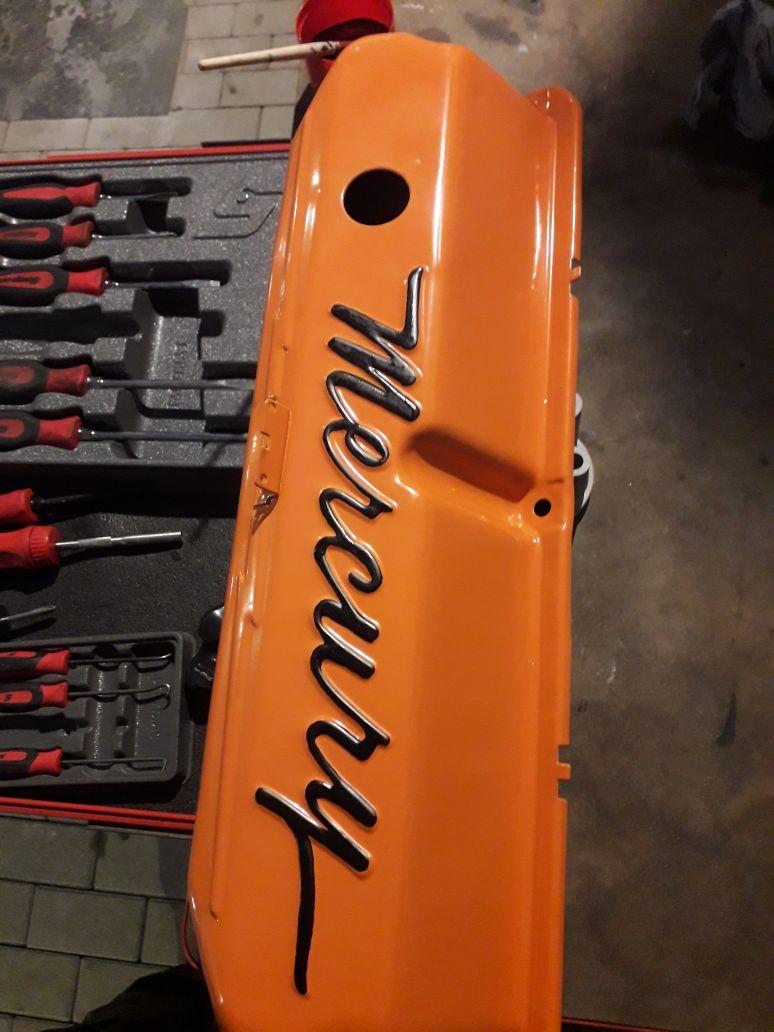
Suche Schriftart für einen US Oldtime Mercury
ich suche die Schrift die man auf dem angehängtem Bild sieht, es gibt mehrere Versionen des  Mercury Logos, wenn jemand eine andere weiss wäre das auch okIMG-20180124-WA0002.jpg.efa7b6c1cb23f1ef45fda83210ba78a3.jpg
Ja, gutes Argument. Es soll eine Beschriftung für den Luftfilterdeckel werden, also völlig anderer Text. Insofern ist der Stil entscheidend ....
Es soll eine Beschriftung für den Luftfilterdeckel werden, also völlig anderer Text.
Solange das nicht genauso ›geprägt‹ sein soll wie der Ventildeckel, brauchst du keinen Font sondern jemanden, der mit ’nem Pinsel umgehen kann. Da sind die letzten Jahre viele aus dem Boden gewachsen. Wo kommst du denn her – vielleicht kann ich dir ’n Tipp geben ..?